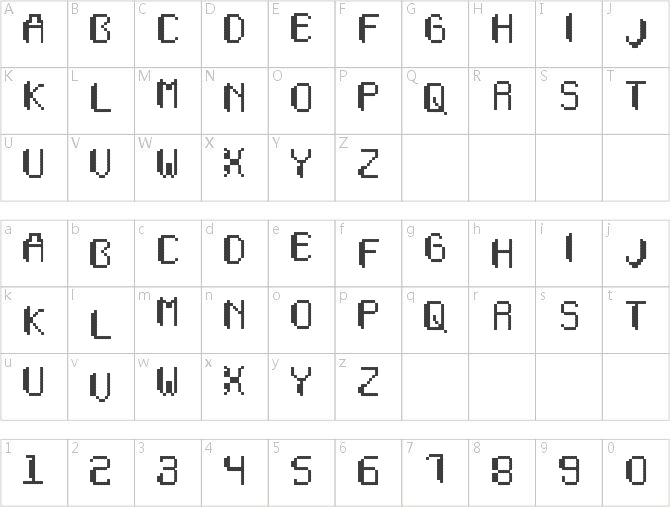
Wapikselo 042015
Wapikselo 042015字體字庫(kù)是一款讓人賞心悅目、百看不厭的英文字體,適合各類(lèi)廣告和產(chǎn)品包裝設(shè)計(jì)應(yīng)用,字體大小0.05MB,格式為ttf字體,上傳用戶是Apple,作者/版權(quán)方為未知